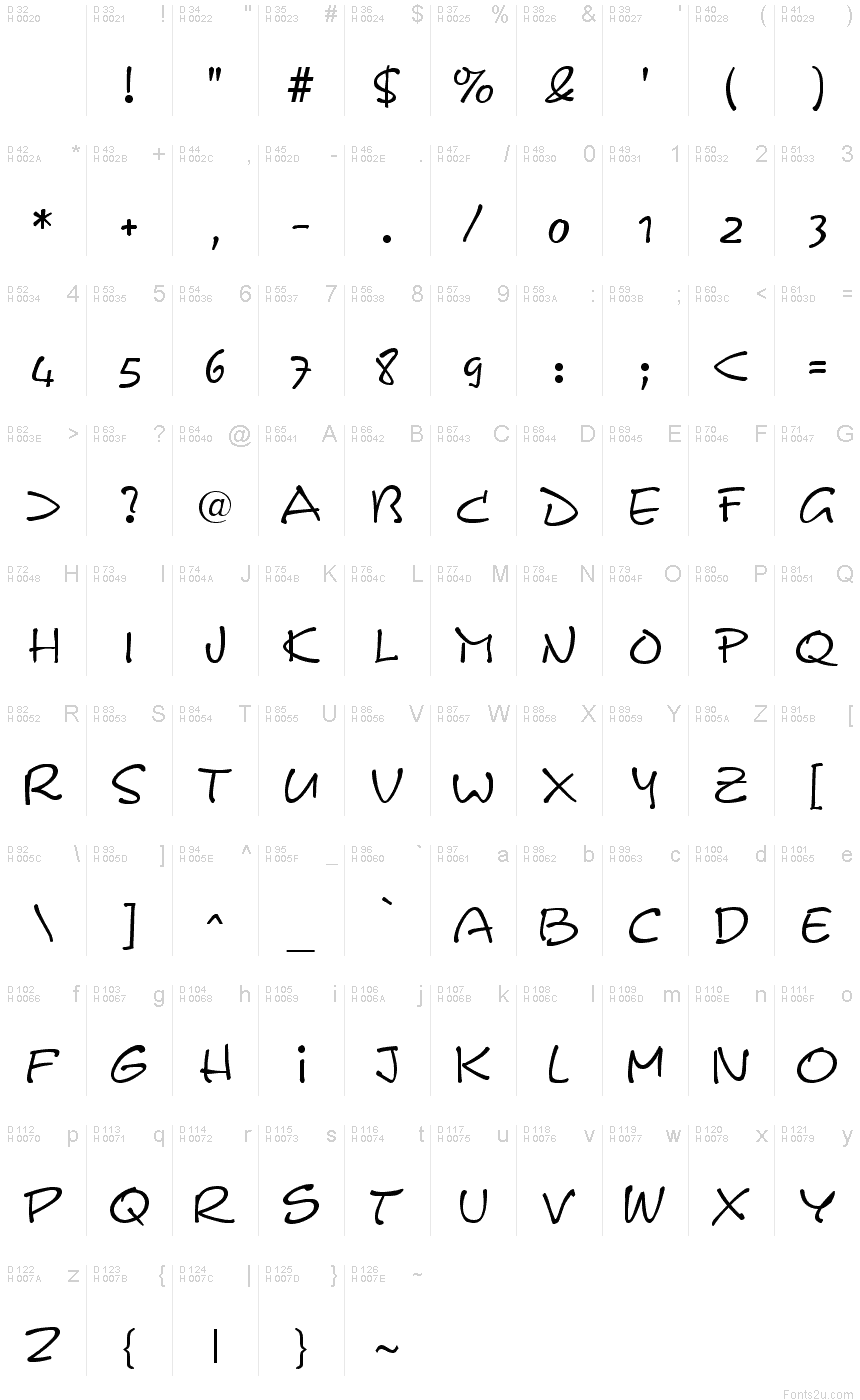
Scribble Regular, un font scritto a mano gratuito, ha quel tocco dinamico e sciolto, tipico di una nota presa al volo con un pennarello. Le lettere appaiono ampie e ariose, con curve morbide, giunture irregolari e un ritmo casuale che rende il testo vivo, tutt'altro che rigido.
Si adatta perfettamente a titoli di album, menu di bar, locandine, etichette di packaging e card per i social media, dove un font con un tocco umano spontaneo risulta più naturale di una scritta troppo curata. Le curve ampie e i tratti leggermente incerti sono ideali per brevi testi o nomi, specialmente quando vuoi che il carattere sembri scritto a mano e non tipografico.